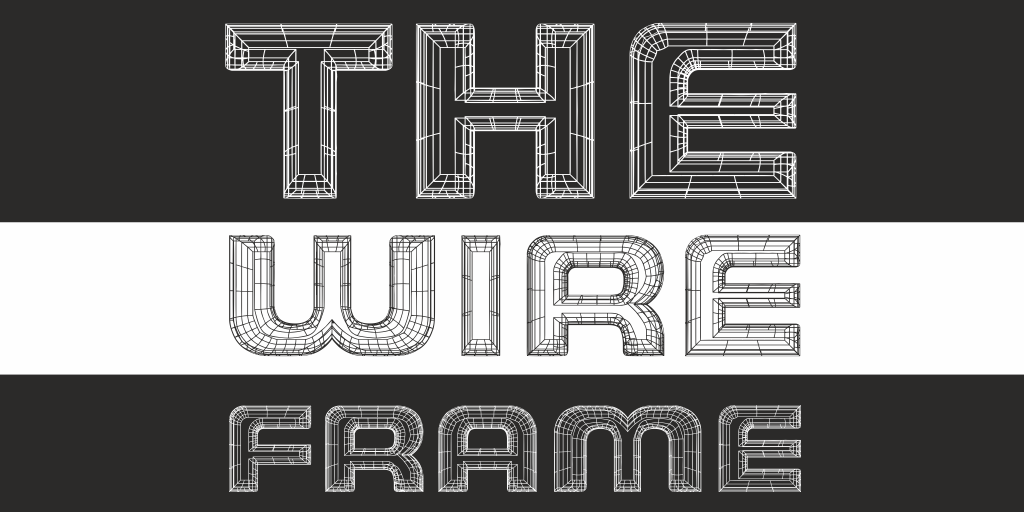
THE WIREFRAME Font – Fonte Grátis
THE WIREFRAME Font
A THE WIREFRAME Font é uma elegante fonte de caráter simples e minimalista criada para adicionar um toque único a projetos decorativos. Essa fonte foi desenvolvida pelo designer Hamilton, trazendo uma variedade de linhas distintas que combinam facilmente com qualquer tipo de projeto visual. Se você está procurando por uma opção moderna e sofisticada, esta font seria perfeita para um design minimalista ou até mesmo um layout gráfico mais elaborado. A THE WIREFRAME Font oferece um conjunto restrito de caracteres para demonstração gratuita, mas se você estiver interessado em usar-a em projetos comerciais, Hamilton espera que visite a www.studiotypo.com. É uma fonte ideal tanto para design de publicidade quanto para criação de logotipos e marcas, ou até mesmo para elementos decorativos como títulos e headlines em páginas web. Essa font é perfeita para quem deseja dar um toque especial a seus projetos digitais, mantendo o equilíbrio entre simplicidade e originalidade. Além disso, seu estilo clean e minimalista combina de forma elegante com diversas paletas de cores e estilos de design, tornando-a uma escolha versátil para qualquer projeto decorativo que você possa imaginar.